Как различить рукописные «б» и «д»: выносы, просветы и проверка в словах
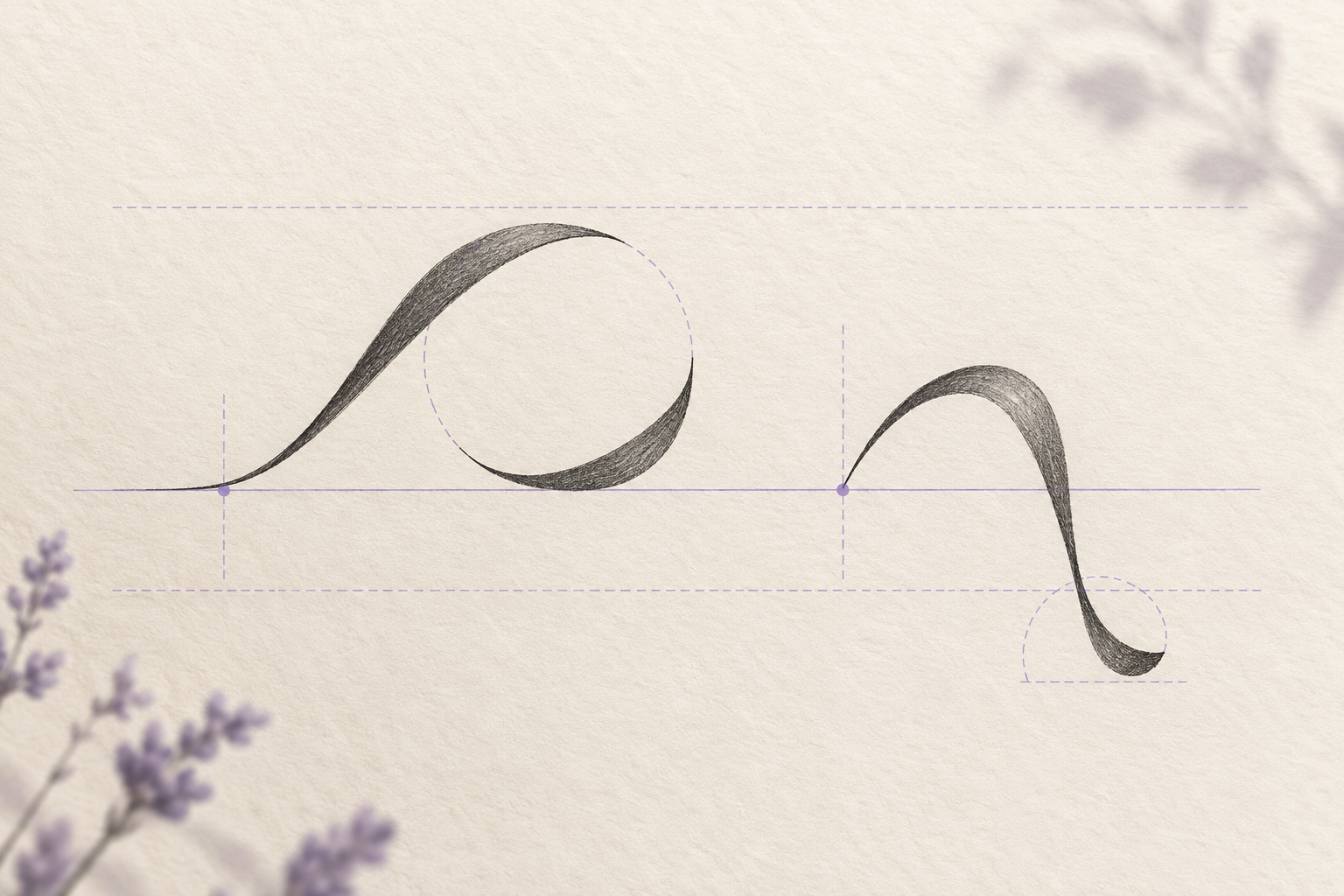
Строчные «б» и «д» в авторском рукописном шрифте легко сблизить, если рисовать их одним движением и не следить, где расположен главный вынос. У «б» узнаваемость часто держится на верхнем подъёме и чаше в зоне строки, у «д» — на основании и нижнем элементе, который уходит под базовую линию. Разберём, как сохранить этот контраст, не ломая единый почерк.
Почему пара требует отдельной проверки
На большом листе автор видит траекторию пера, помнит, какую букву задумал, и достраивает контур мысленно. Читатель получает только готовый силуэт. Когда почерк переводят в набор знаков, движение руки превращается в статическую форму, а привычные подсказки — направление письма, последовательность штрихов и соседние буквы — работают не всегда. Поэтому проверять нужно не намерение автора, а то, что можно увидеть без объяснения.
Буквы «б» и «д» особенно полезно сравнить рядом: их можно построить из округлой части, вертикального штриха и соединения, но распределены эти элементы по-разному. В одном рисунке верхняя часть «б» может оказаться похожа на петлю «д», в другом нижний вынос «д» теряется на линии набора. Это не делает пару по природе неразличимой: риск возникает, когда различительный признак слишком слаб, скрыт соседним соединением или исчезает при уменьшении.
Какие элементы создают различие
Сначала мысленно уберите цвет, фактуру пера и скорость письма. Оставьте внешний контур и положение относительно трёх ориентиров: верхней линии строчных, базовой линии и зоны под строкой. В разных почерках конкретное устройство букв варьируется; задача не в том, чтобы привести их к единственному школьному образцу, а в том, чтобы в вашей гарнитуре две формы не зависели от догадки.
У «б» важны подъём и чаша
В распространённой печатной конструкции строчная «б» имеет верхний элемент, который поднимается над корпусом строчных, и округлую нижнюю часть. В рукописном начертании внешний контур может быть проще, соединён с соседней буквой или иметь наклон, но верхняя зона обычно остаётся важной подсказкой. Посмотрите, читается ли подъём как осмысленная часть глифа, а чаша — как отдельная опора, а не как петля, случайно замкнувшаяся у стойки.
Если верхняя петля слишком мала, она может превратиться в утолщение или исчезнуть в штрихе. Если чаша раскрыта там же, где ожидается соединение, граница буквы становится неясной. Не обязательно увеличивать контраст до декоративного жеста: часто достаточно сделать яснее место перехода между подъёмом и округлой частью, проверить высоту петли и сохранить внутренний просвет.
У «д» важны основание и нижняя зона
Кириллическая «д» допускает несколько конструктивных вариантов: в частности, форма может иметь нижние опоры или уходящий вниз элемент. В авторском шрифте допустима собственная пластика, но читателю нужен устойчивый признак, по которому глиф не превращается в округлую букву соседней строки. Проверьте, не обрывается ли нижний элемент слишком близко к базовой линии и не сливается ли он с выходом к следующему знаку.
Смотрите не только на длину выноса. Его положение, ширина основания, направление изгиба и связь с чашей могут быть важнее. Если «д» построена широко, а нижняя часть почти не выходит из строки, силуэт может выглядеть как «а» или как незаконченная петля. Если вынос чрезмерно длинный, он конкурирует с нижними элементами соседних букв и ухудшает ритм строки. Ищите узнаваемое, но сдержанное отличие.
Сравните просветы, а не только штрихи
Положите «б» и «д» рядом и посмотрите на белые участки внутри и вокруг форм. У одной буквы может быть открытая чаша, у другой — более компактный внутренний просвет; основание «д» задаёт пространство под строкой. Если внутренние отверстия обеих форм одинаковы, а верх и низ почти совпадают по высоте, контуры могут начать восприниматься как варианты одного знака.
Просвет — полноценный элемент рисунка, а не пустое место, которое можно оставить на потом. Сравните его ширину на самом узком участке, площадь относительно штриха и то, где он открывается. При уменьшении тонкая щель легко закрывается, поэтому нельзя оценивать только крупный мастер-рисунок.
Практический алгоритм проверки
Шаг 1. Установите ориентиры строки
На одном листе проведите верхнюю линию строчных, базовую линию и линию, отмечающую допустимую глубину нижних выносов. Не задавайте абсолютные нормы по сетке: это временная разметка для сравнения, а не требование одинаковой высоты у всех букв. Нарисуйте «б» и «д» в одном масштабе, тем же инструментом и с тем же наклоном, что и соседние глифы.
Шаг 2. Разберите силуэты по зонам
Сделайте рядом три копии каждой буквы. В первой отметьте верхний контур, во второй — внутренний просвет, в третьей — опору относительно базовой линии. Спросите себя, какая одна деталь первой позволяет назвать знак. Если ответ приходится давать через историю рисования — «я здесь провёл перо вниз» — признак не виден в готовом изображении.
Нет, сначала определите источник сбоя. Иногда достаточно поправить конкретное соединение, интервал или одну пропорцию глифа. После любой локальной правки перепроверьте соседние формы, чтобы сохранить общий ритм.
Различие между рукописными «б» и «д» можно построить на том, где находятся их выразительные части: верхнем подъёме и чаше одной буквы, основании и нижней зоне другой. Сравните силуэт, просветы, соединения и рабочий размер; проверяйте одну гипотезу за раз. Когда пара читается без подсказки и сохраняет характер почерка, можно собрать шрифт и проверить его на собственном тексте.